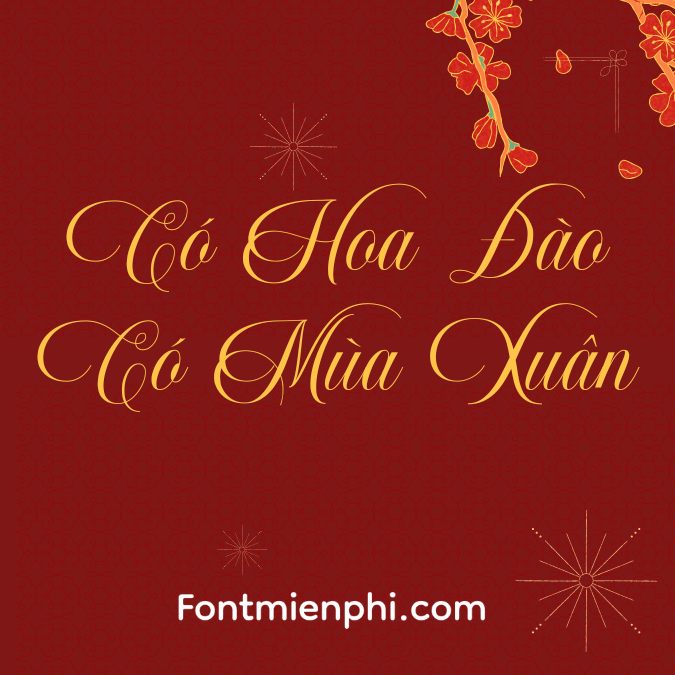
Font Việt Hóa 1FTV VIP Nathalia – Phông Chữ Sang Trọng, Độc Đáo Dành Cho Thiết Kế
Giới Thiệu Font VIP Nathalia
Font Việt Hóa 1FTV VIP Nathalia là bộ font chữ nghệ thuật cao cấp, được thiết kế tỉ mỉ với nét chữ thanh lịch, phù hợp cho các dự án thiết kế sang trọng như logo, card visit, poster, và các ấn phẩm cao cấp.
✅ Đầy đủ bộ ký tự Tiếng Việt (TV Standard)
✅ Phong cách hiện đại, thanh lịch
✅ Dễ dàng sử dụng trong in ấn & thiết kế
Đặc Điểm Nổi Bật Của Font Nathalia
1. Thiết Kế Tinh Tế, Đẳng Cấp
• Nét chữ mềm mại, kết hợp giữa nét thanh và đậm tạo điểm nhấn ấn tượng.
• Phù hợp với các thiết kế thời trang, nhà hàng, mỹ phẩm, và thương hiệu cao cấp.
2. Hỗ Trợ Đầy Đủ Tiếng Việt
• Font đã được Việt hóa chuẩn, hỗ trợ đầy đủ dấu và ký tự đặc biệt (ă, â, ê, ô, ơ, ư, đ).
3. Đa Dạng Ứng Dụng
• Thiết kế logo sang trọng
• In ấn card visit, menu, bao bì
• Làm poster, banner quảng cáo
• Thiết kế profile công ty, tạp chí thời trang
Kết Luận